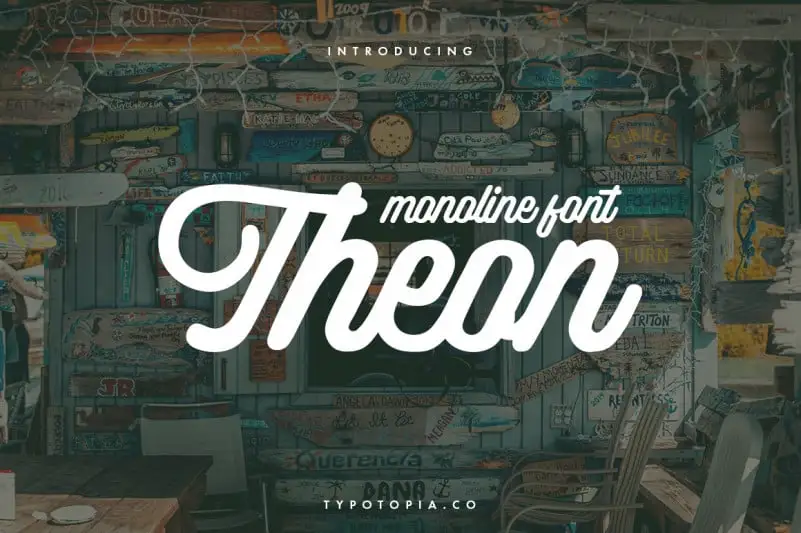
A Theon Handwritten Font é uma deliciosa mistura de letras escritas à mão que flui naturalmente com um toque elegante. Ela combina a personalidade única e eterna dos textos artesanais para se tornar perfeita para qualquer projeto especial. Experimente fazer sua marca ou design único, usando essa fonte para criar designs excepcionais. A Theon Handwritten Font não apenas faz seu trabalho, mas traz uma sensação de autenticidade e originalidade que é difícil encontrar em outros tipos de escrita. Seja para o seu site pessoal, a revista da sua empresa ou até mesmo um convite especial, a Theon Handwritten Font garantirá que cada projeto seja único e memorável.